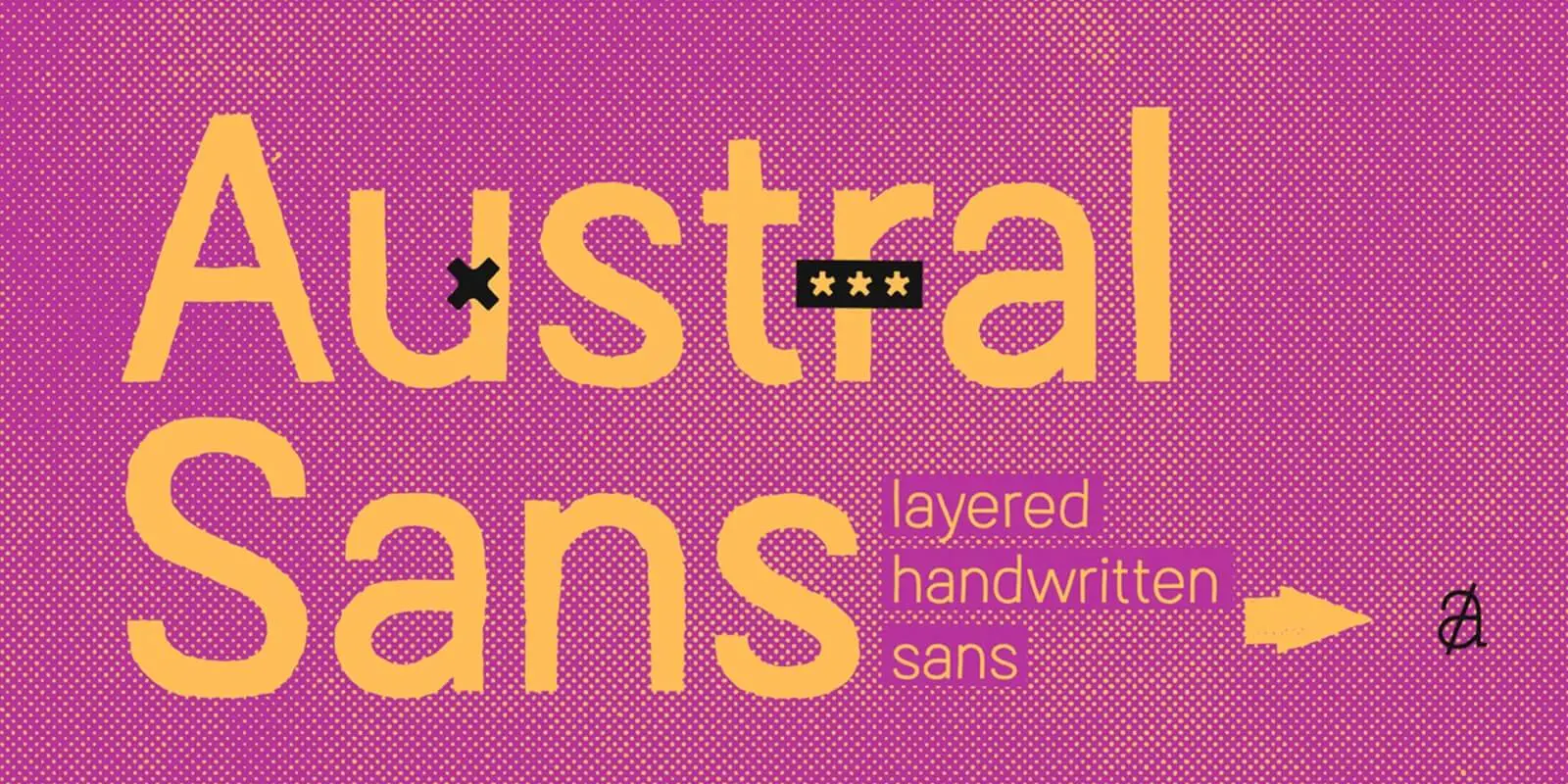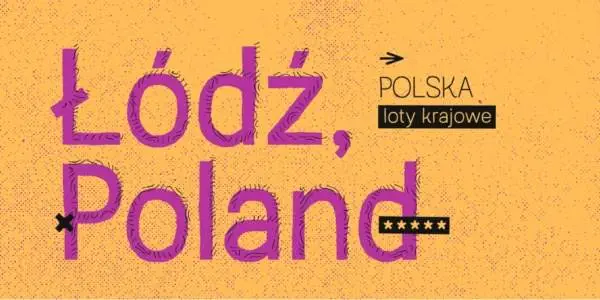
Font Austral Sans là một phông chữ nhiều lớp vẽ tay được thiết kế bởi Antipixel. Dựa trên phiên bản Slab , nó là một phần của họ kiểu Austral.
Điều này không làm cho tác phẩm của bạn trở nên độc đáo và đáng chú ý, bởi vì khả năng kết hợp các kết cấu và phong cách tạo ra kết quả đặc biệt. Font Austral Sans có ba trọng lượng, Thường, Nhẹ và Mỏng, tất cả đều có chung kiểu dáng cong queo với các nét và đường viền không đều.
Vì những lý do này, phông chữ này có thể được sử dụng trong rất nhiều dự án, chẳng hạn như logo & thương hiệu, văn phòng phẩm, bìa sách, thiết kế tạp chí, bản in & thẻ quần áo, bao bì, video hoạt hình, v.v.!
Font Austral Sans có ba bộ chữ cái viết hoa và viết thường để tránh lặp lại cùng một mẫu ký tự và tạo cho phông chữ cảm giác viết tay tự nhiên hơn.
Điều này được bao gồm trong Open-Type Contextual Alternatives , áp dụng thay thế tự động các glyph miễn là các tính năng Open-Type được kích hoạt.
Ngoài ra, Austral Sans cung cấp các tính năng Loại mở khác, chẳng hạn như **Kiểu thay thế phong cách, Chữ ghép, Chữ ghép tùy ý, Phân số, Chỉ số trên, Chỉ số dưới, Mẫu số, Tử số, Suy luận khoa học & Kerning. **
Phông chữ này có phạm vi bao phủ nét chữ rất lớn và có thể được sử dụng bằng nhiều ngôn ngữ, bao gồm tiếng Anh, tiếng Tây Ban Nha, tiếng Bồ Đào Nha, tiếng Ý, tiếng Pháp, tiếng Đức, tiếng Ba Lan, tiếng Séc, tiếng Việt, tiếng Phần Lan, tiếng Iceland , cùng nhiều ngôn ngữ khác.